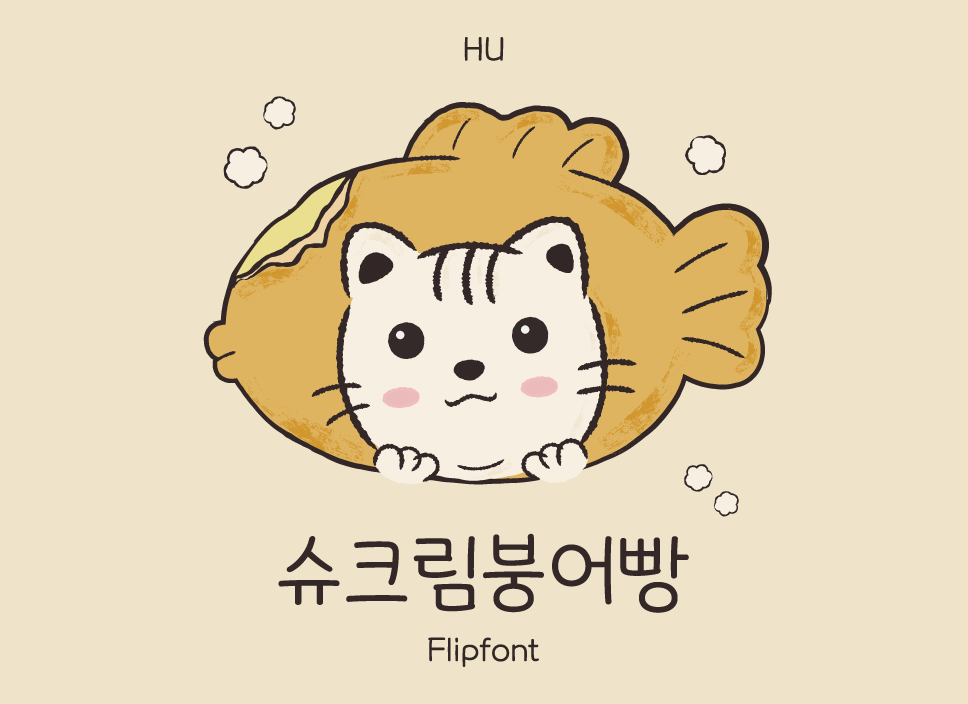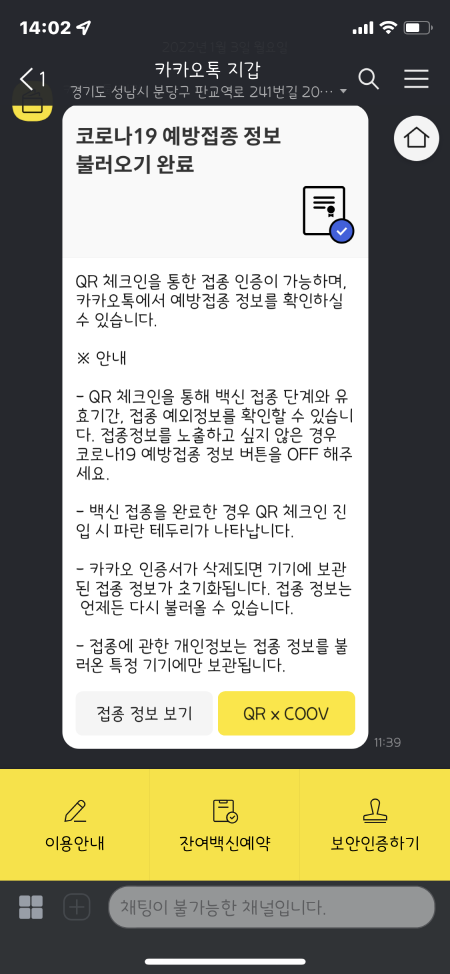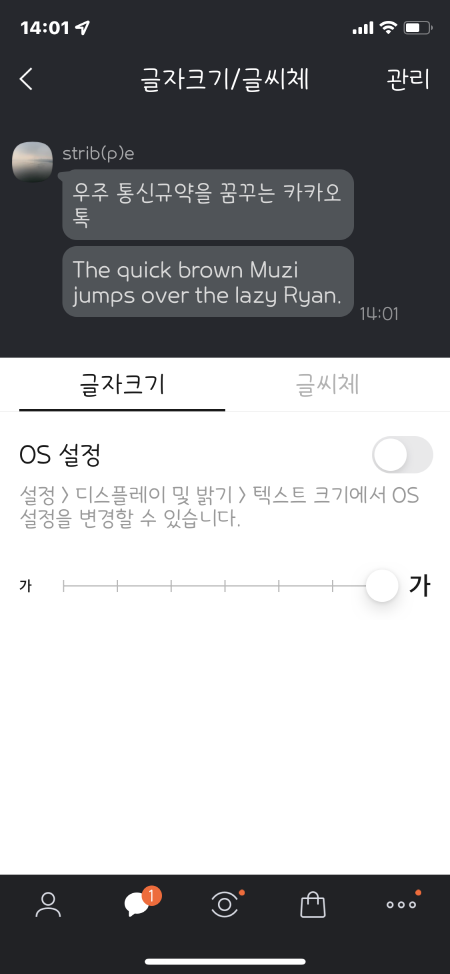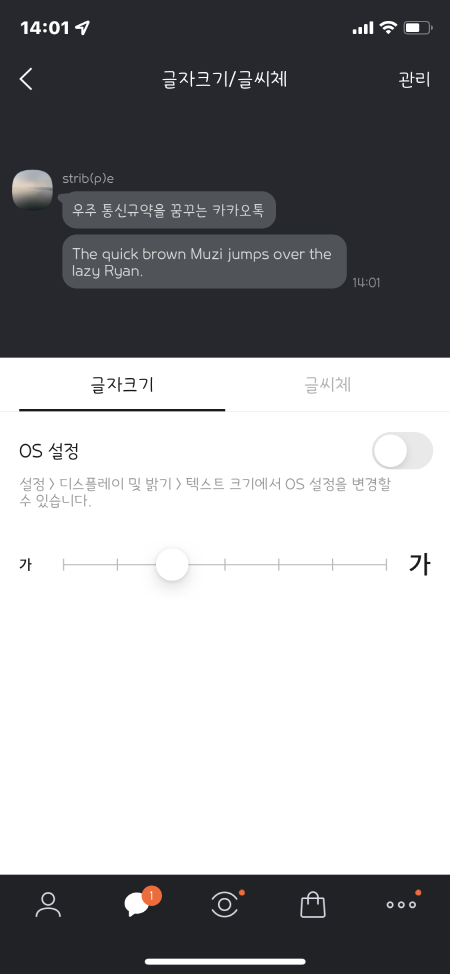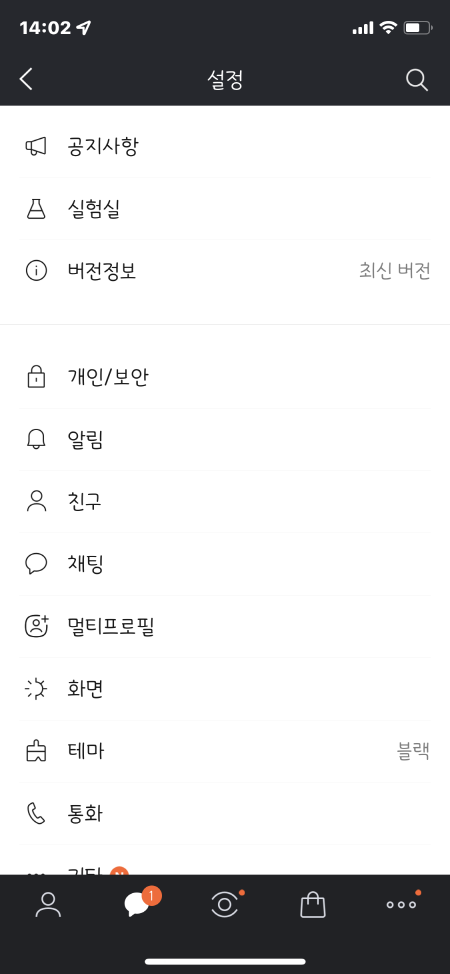
곡선의 형태를 유지하여 부드럽고 귀여운 이미지를 강조하였습니다,
'붕'의 'ㅇ', '어'의 'ㅇ', '빵'의 'ㅇ'
문자의 조합에 따라 다양한 형태를 지니고 있어 더욱 손글씨에 가까운 느낌을 나타냅니다.
전체적으로 곡선을 이용하는 서체이다 보니 특수기호를 이용한 이모티콘도 귀엽습니다.
곡선의 형태를 유지하여 부드럽고 귀여운 이미지를 강조하였습니다,
'붕'의 'ㅇ', '어'의 'ㅇ', '빵'의 'ㅇ'
문자의 조합에 따라 다양한 형태를 지니고 있어 더욱 손글씨에 가까운 느낌을 나타냅니다.
전체적으로 곡선을 이용하는 서체이다 보니 특수기호를 이용한 이모티콘도 귀엽습니다.